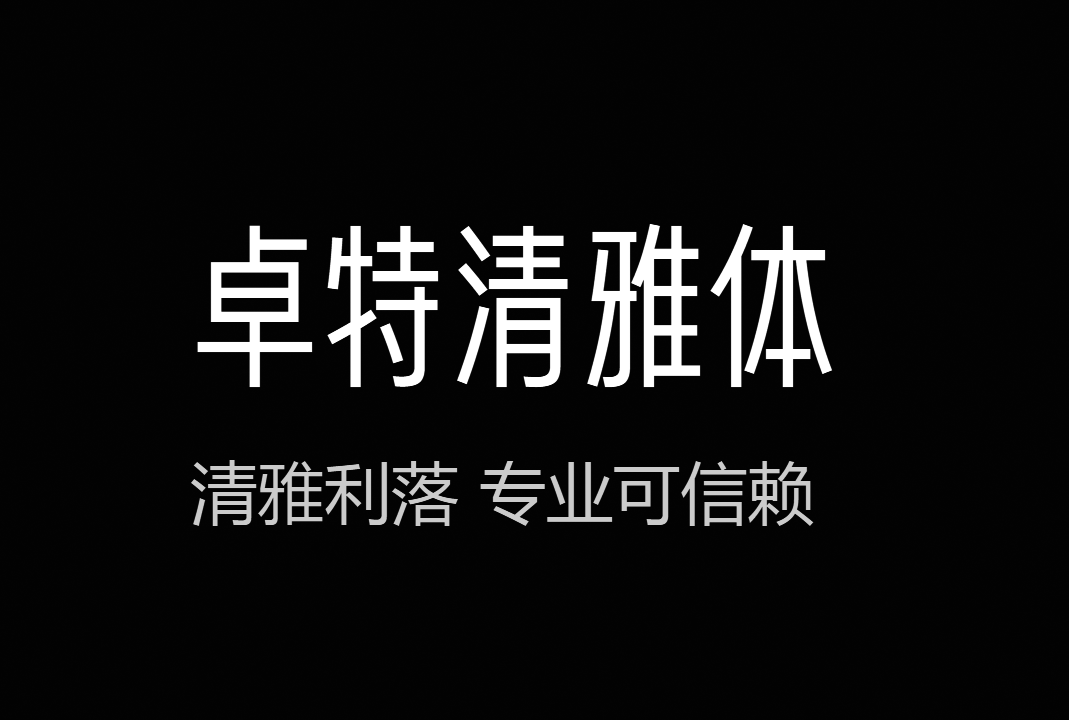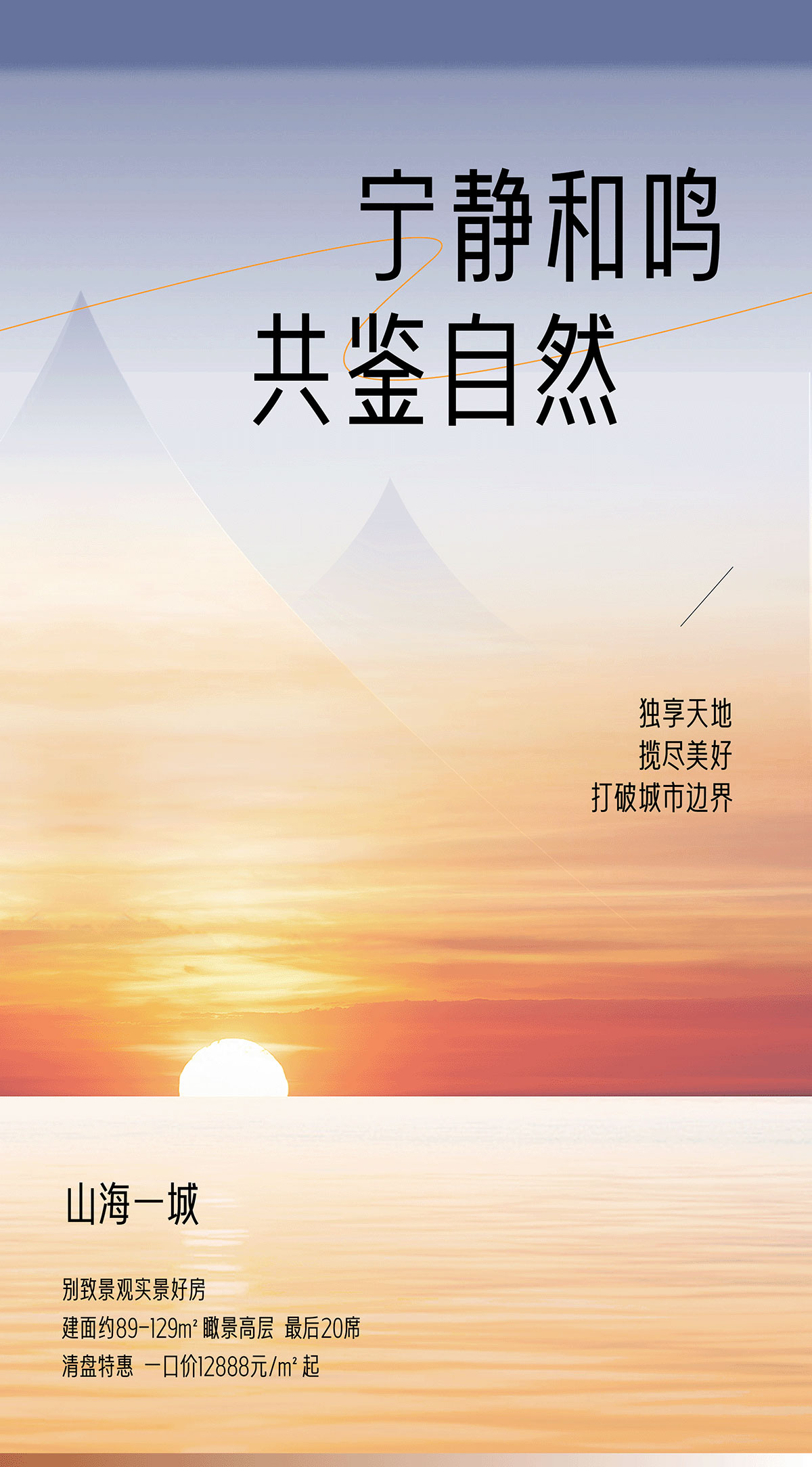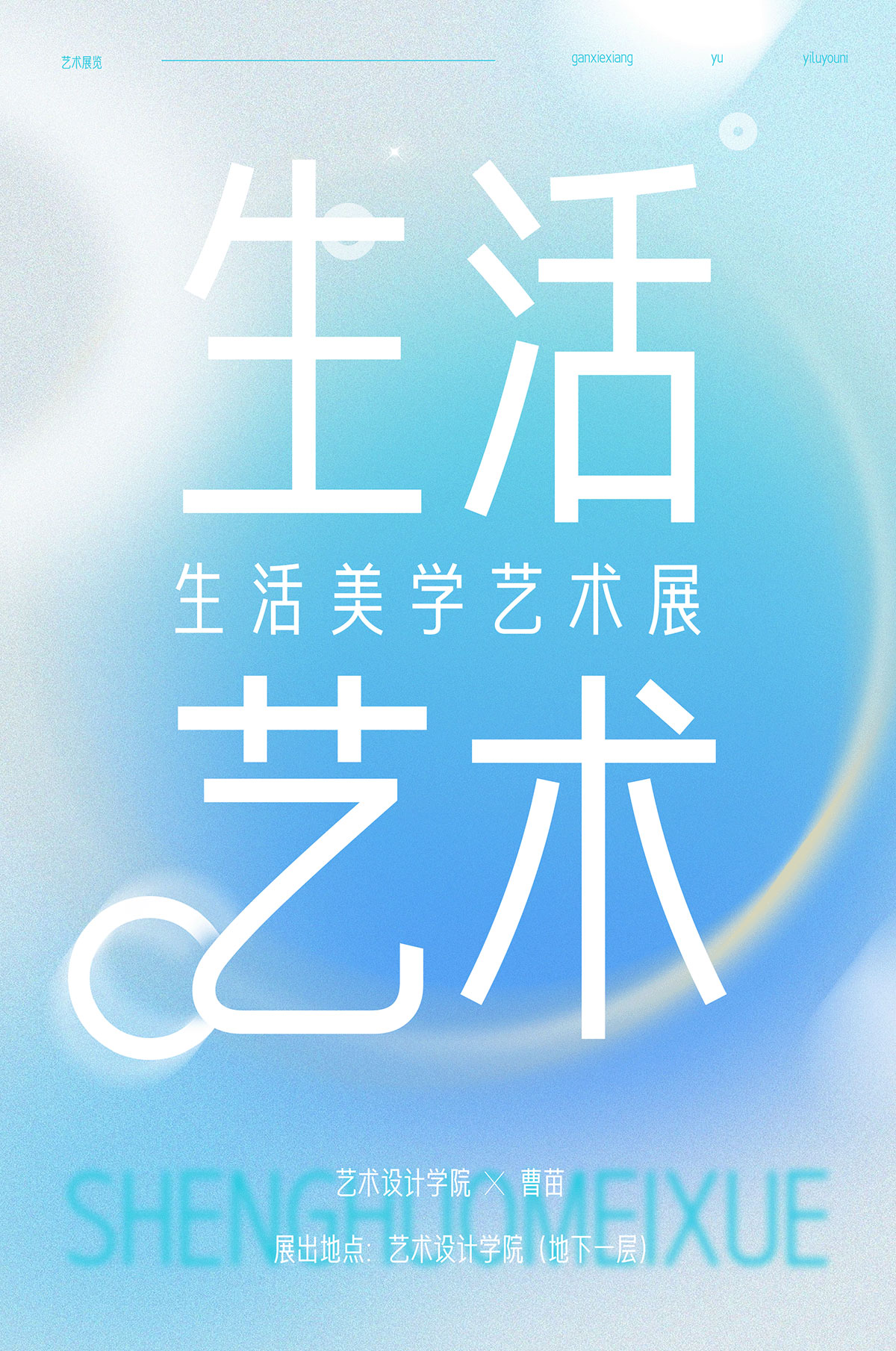
卓特清雅体是由卓特视觉携手国内知名字体设计师刘兵克,为创意人群打造三款风格迥异的免费字体之一。
卓特清雅体字形瘦长挺拔,线条细致干净,具有强烈的现代化气息与技术审美。字面适度均衡,结构稳定,适合各类专业场景使用。包含 GB2312-80 标准中的 6763 个简体汉字及 420 个常用字符,共收录 7183 个字符,可满足日常办公、设计创作、品牌宣传等多元场景的字体使用需求。